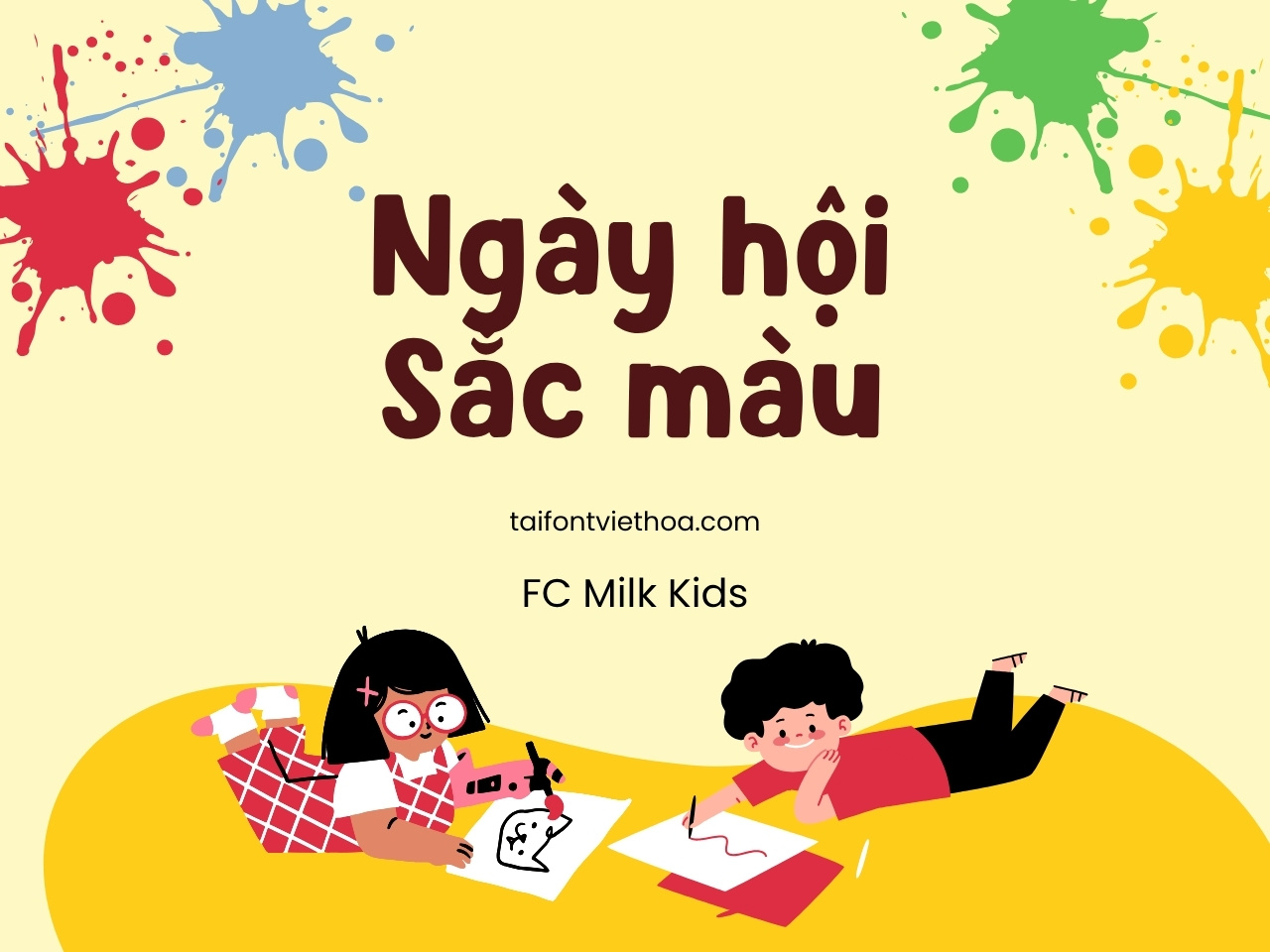
Font việt hóa FC Milk Kids
Font việt hóa FC Milk Kids thiết kế Poster
Tác giả Font: Rizky Awaludin
Giới thiệu về font Milk Kids và phiên bản Việt hóa
FC Milk Kids là một phiên bản Việt hóa độc lập từ font gốc “Milk Kids” do nhà thiết kế Rizky Awaludin sáng tạo. Font mang phong cách viết tay ngộ nghĩnh, mềm mại và giàu cảm xúc – gợi nhớ đến nét chữ của trẻ thơ. Khác với bản “1FTV VIP Milk Kids”, phiên bản FC Milk Kids được Việt hóa theo hướng giữ nguyên độ tự nhiên của nét bút tay nhưng đảm bảo sự trọn vẹn trong bảng mã Unicode dành cho tiếng Việt. Font gốc từng được phát hành trên Creative Fabrica và hỗ trợ hơn 60 ngôn ngữ dùng bảng chữ cái Latin, rất phù hợp với các thiết kế hướng đến thiếu nhi, sản phẩm thực phẩm hay dự án sáng tạo giàu cảm xúc. Font này được taifontviethoa.com chọn lọc, kiểm duyệt và phân phối, nhằm đáp ứng nhu cầu sử dụng một kiểu chữ vui nhộn, gần gũi, và dễ áp dụng trong các dự án mang tính sáng tạo và cảm xúc.
Đặc điểm thiết kế và ứng dụng của FC Milk Kids
FC Milk Kids mang phong cách handwritten (viết tay) đặc trưng với những nét chữ không đều, mềm mại và ngộ nghĩnh. Các ký tự thường có độ nghiêng nhẹ, mang lại cảm giác tự nhiên và gần gũi như chữ viết tay của trẻ nhỏ. Những đường nét tròn trịa, đáng yêu kết hợp cùng khoảng cách chữ hợp lý khiến font cực kỳ dễ đọc và truyền cảm hứng tích cực cho người xem.
Font này lý tưởng cho các dự án liên quan đến trẻ em như thiết kế poster trường học, bìa sách thiếu nhi, thực đơn nhà hàng cho bé, hoặc các sản phẩm handmade, đồ chơi và quà tặng sáng tạo. Ngoài ra, FC Milk Kids còn phù hợp trong thiết kế nhận diện thương hiệu ngành ẩm thực, spa, đồ uống, và ứng dụng trong lĩnh vực quảng cáo hoặc bảng hiệu độc đáo mang tính vui tươi.